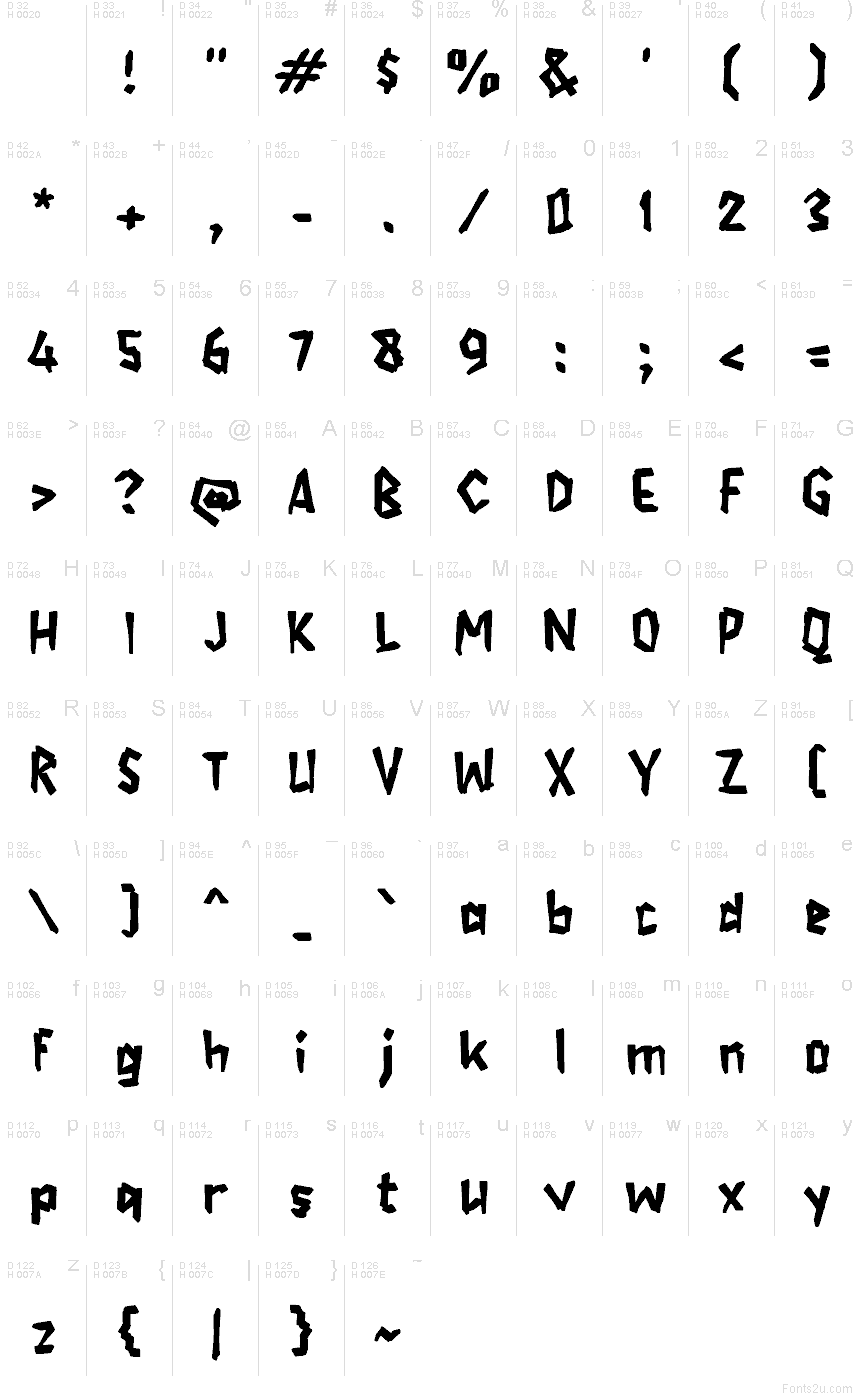
Raedan od Wep to darmowy krój pisma typu display, utrzymany w stylistyce surowych pociągnięć pędzla, emanujący wyrazistym, ręcznie malowanym charakterem. Litery wyglądają jak wycięte z grubych śladów markera – z nierównymi krawędziami, wąskimi łączeniami i lekko plemiennym rytmem typowym dla ręcznie robionych plakatów, co sprawia, że całość pozostaje surowa i daleka od matematycznego porządku.
Dzięki temu świetnie sprawdzi się na grafikach dla zespołów, plakatach do horrorów, tytułach gier, okładkach zinów czy w streetwearze, gdzie krótkie słowa potrzebują charakteru, a nie wygładzenia. Jako darmowy font, Raedan sprawdza się również w szkicach logo, otwarciach rozdziałów czy przyciągających wzrok nagłówkach, ponieważ jego wielkie litery mają ciężką, ręcznie wykonaną wagę, nie wpadając przy tym w zbyt sterylne rejony typografii reklamowej.